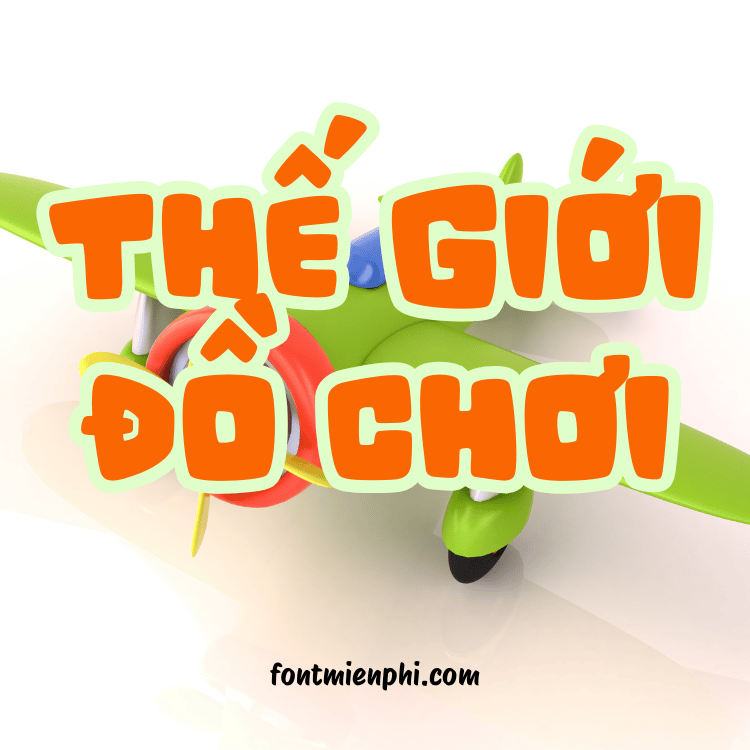
Font Việt Hóa Spenbeb & FMP VIP – Phong Cách Độc Đáo Cho Thiết Kế
Font Việt hóa Spenbeb và FMP VIP là hai bộ font chữ đẹp, hỗ trợ tiếng Việt, mang đến phong cách hiện đại, sáng tạo cho các dự án thiết kế. Với nét chữ mềm mại, thanh lịch, Spenbeb phù hợp với thiết kế logo, poster, bìa sách, trong khi FMP VIP nổi bật với các kiểu chữ đa dạng, từ cổ điển đến phá cách, giúp tạo điểm nhấn cho mọi ấn phẩm.
Đặc điểm nổi bật Font Việt hóa Font Spenbeb, Font FMP VIP :
✔ Nét chữ tinh tế – Đa dạng phong cách từ sang trọng đến cá tính.